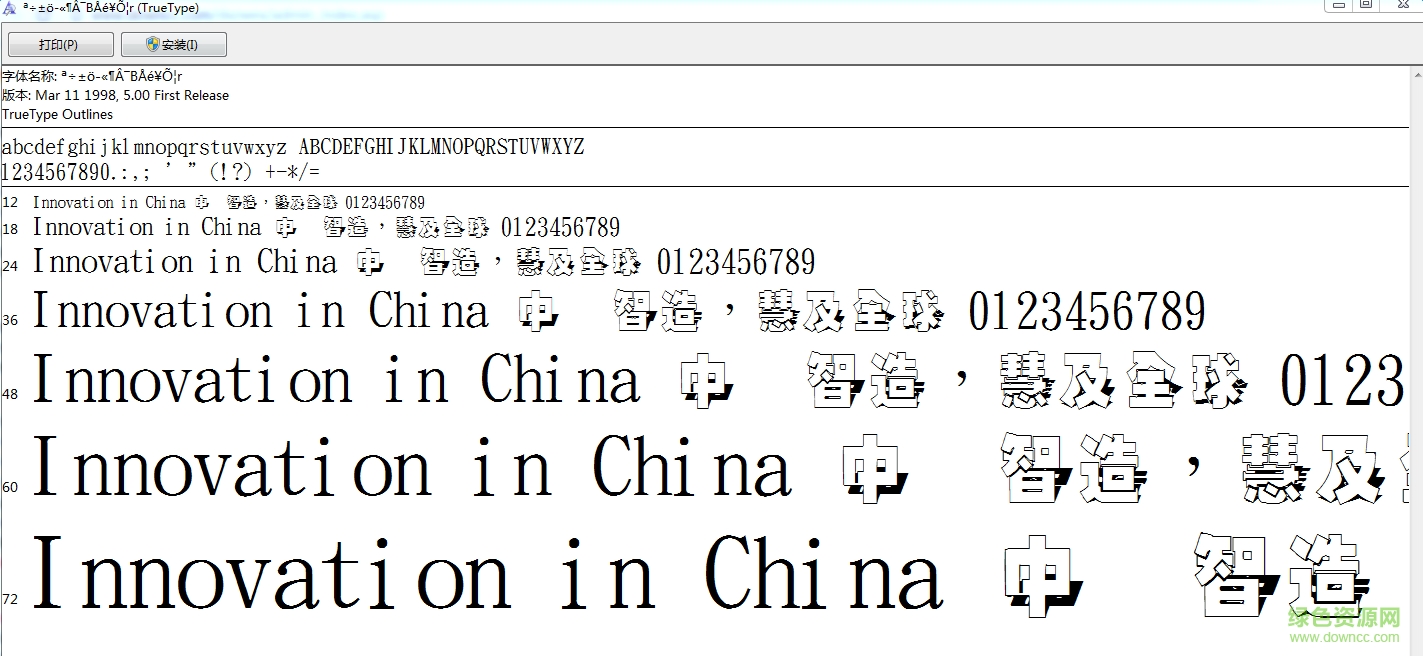
金梅重黑浮體白字字體外觀上看起來(lái)和立體化。這款字體文字效果相比較傳統(tǒng)的黑體、宋體都比較突出的,常被用于設(shè)計(jì)廣告大標(biāo)題使用!需要的用戶快來(lái)拿走吧!
金梅重黑浮體白字是一款金梅類的浮體字,字體效果比較立體,金梅類浮體字給人立體效果十足的感覺,深受廣大書法家和年輕人的喜愛,還有更多好看字體盡情期待,歡迎到綠色資源網(wǎng)下載體驗(yàn)!